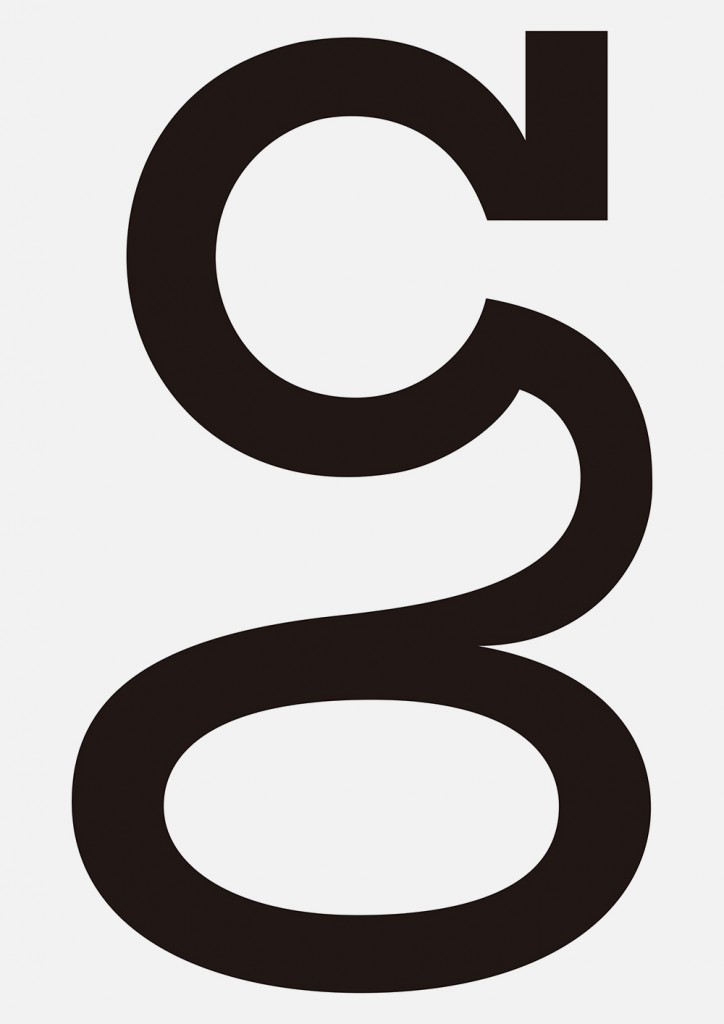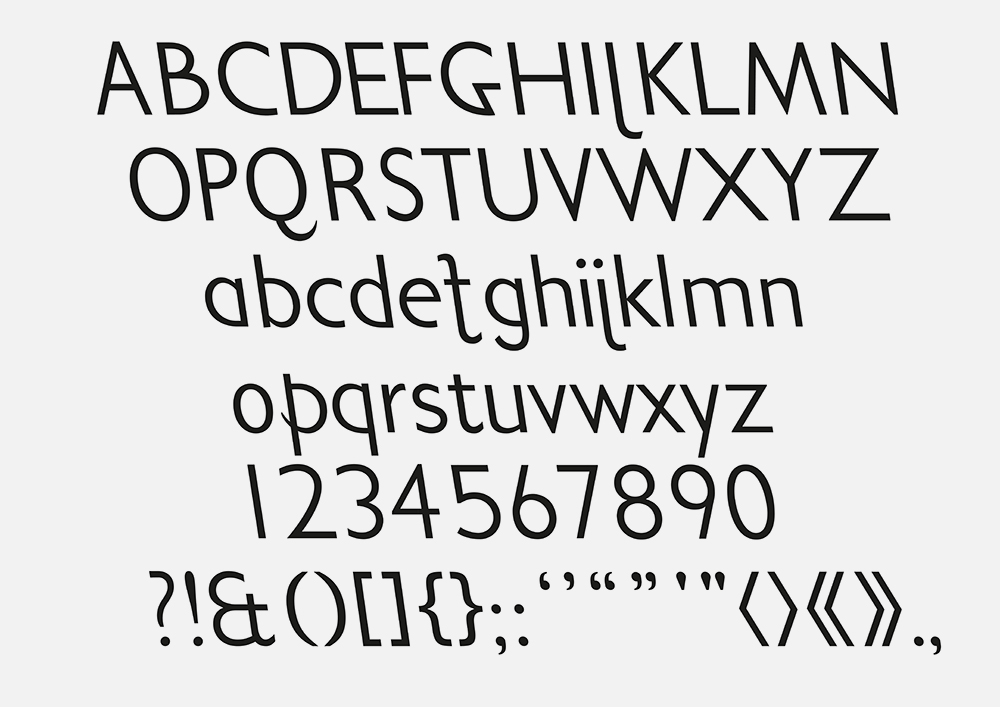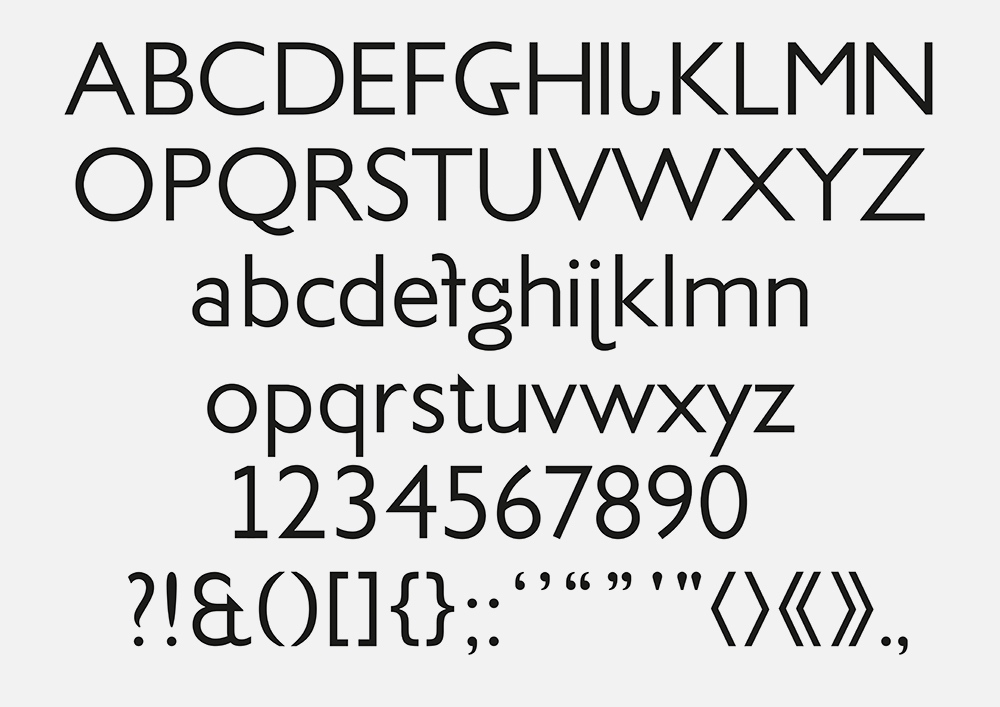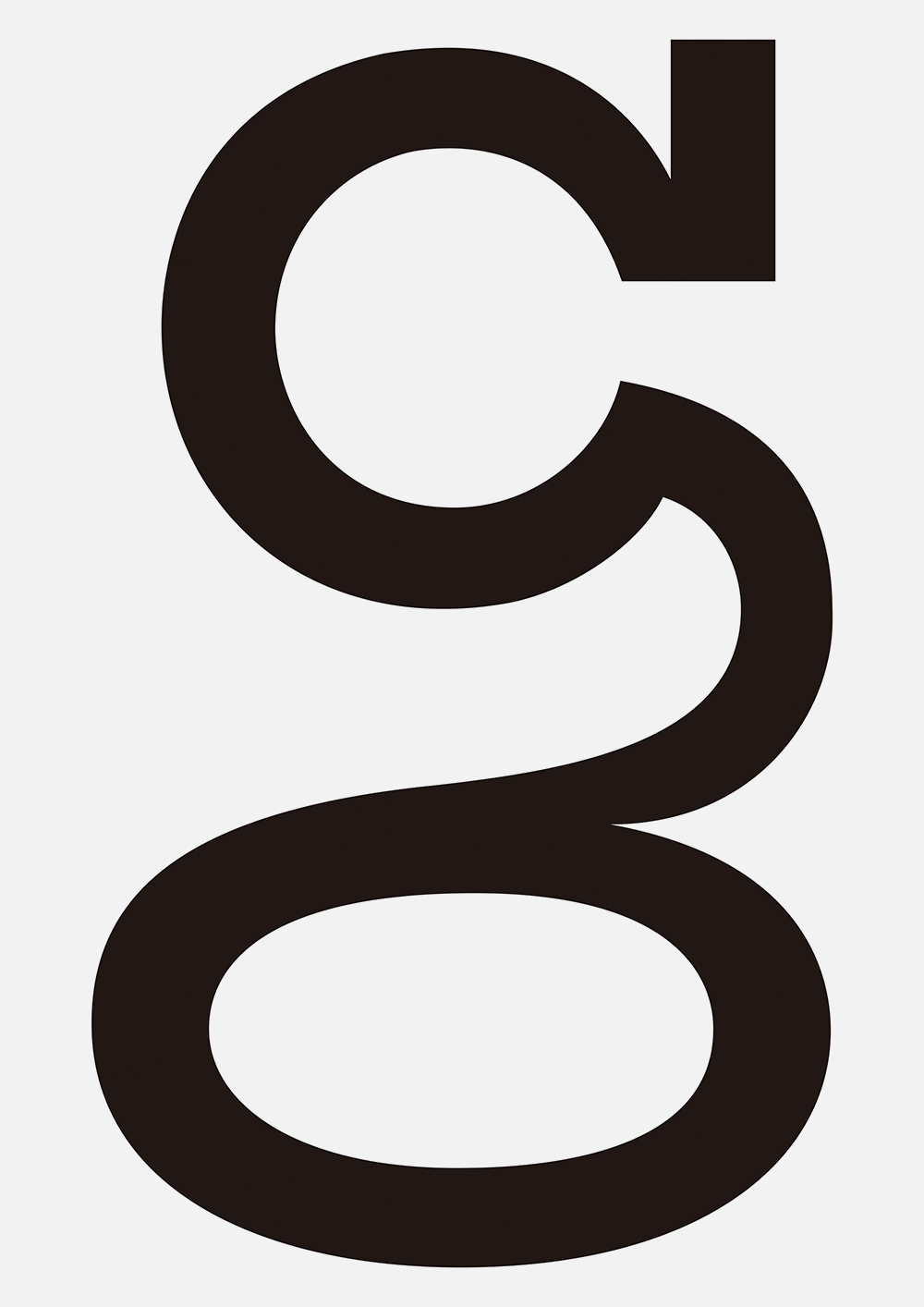
왼손잡이 서체 : LEFT HANDED GILL
올해 국내 대학 시각디자인 관련 학과 졸업전시에서 발견한 작품을 소개한다.
LEFT HANDED GILL
왼손잡이의 필기 습관을 반영한 서체입니다. 구체적인 관련 연구 과정을 소개해주세요.
이탤릭체의 기울어짐은 오른손잡이의 필기 습관을 반영한 결과라는 것을 알게 되었고, 이 기울어짐의 근거에 관한 탐구에서 비롯된 이 프로젝트는 왼손잡이 필기습관을 반영한 서체 제작으로 이어졌습니다. 글자가 좌측으로 기울며, 문장이 위쪽으로 쏠리고, 종이를 직각으로 몸 안쪽으로 돌려놓고 쓴다는 왼손잡이의 특징이 기억에 남습니다. 그렇게 왼손잡이가 오른손잡이처럼 쓰기 위해서는 이상한 모습으로 글을 써야 한다는 것이죠.
연구를 진행하던 중 왼손잡이를 위한 글쓰기 교본이 있다는 것을 알았는데, 그 책은 글쓰기를 처음 배우는 왼손잡이 학생들이 알파벳을 쓸 때 더 편한 방법을 알려주고 있었습니다. 그런데 몇몇 알파벳에서 획을 쓰는 방향이 반대더군요. 그 부분을 이 서체에 반영했습니다.
전통적인 서체 디자인에서는 전체 모음에 있어 시각적 균형을 중요시하죠. 필기 습관을 반영한 서체를 제작하면서 이에 대한 어려움은 없었나요?
최초의 휴머니스트 계열 산세리프 서체인 <길 산스>를 기반으로 서체를 만들어보는 것이 온전한 서체 한 벌을 제작해본 경험이 없는 저에게 의미적, 현실적으로 적합했습니다. 이 선택으로 시각적 균형을 맞추는 것에 대한 어려움을 상당 부분 해소했어요. J나 f와 같이 전통적인 알파벳과 반대 형태를 띠는 활자의 경우, 가로획 필기 방향과 같이 세로획이 둥글게 말리는 방향도 정해졌다는 것에서 비롯되었습니다. 오른손잡이와는 반대인 왼손잡이의 가로획 필기 방향을 기준으로 달라질 서체의 형태에 대한 고민 끝에 반전된 형태로 디자인한 것이죠. 활자체의 모양을 바꿀 때는 논리적이라 여겨지는 근거를 기준으로 삼긴 하지만 이 프로젝트에서만큼은 개인적 상상력이 유효했습니다.
과정 중 얻은 배움 중 기억에 남는 것이 있다면요?
지도교수였던 최성민 교수님이 소개해주신 신세카이 타이포 연구회(SHINSEKAI TYPE STUDY GROUP)의 서체 연구,〈가로쓰기 가나(THE FORMATION OF “NEW” KANA WRITTEN HORIZONTALLY)> 소개 영상(YOUTU.BE/COYSUJUKO)이 기억에 남습니다. ‘세로쓰기를 기반으로 형성된 일본 가나 문자가 가로쓰기 문자로 진화했다면 어떤 모습일까?’를 주제로 하는 연구입니다. 서체의 모양이 결정되는 과정에 대해 많이 배웠고, 그에 따라 이번 프로젝트에 큰 도움이 되었습니다.